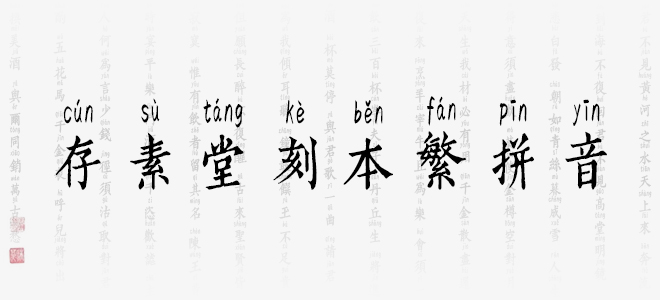
存素堂刻本繁拼音是一款基于存素堂刻本繁字體的基礎(chǔ)上,添加了拼音標(biāo)注效果的拼音字體,筆畫流暢飛揚(yáng),結(jié)體左緊右松,開合對比強(qiáng)烈,進(jìn)一步強(qiáng)化了動感。整套字體有如一氣呵成,行筆迅捷華麗,其個性浪漫灑脫,適用于現(xiàn)代詩歌、短文的排版,以及文化、商業(yè)類品牌的廣告語設(shè)計(jì)。
存素堂刻本繁拼音